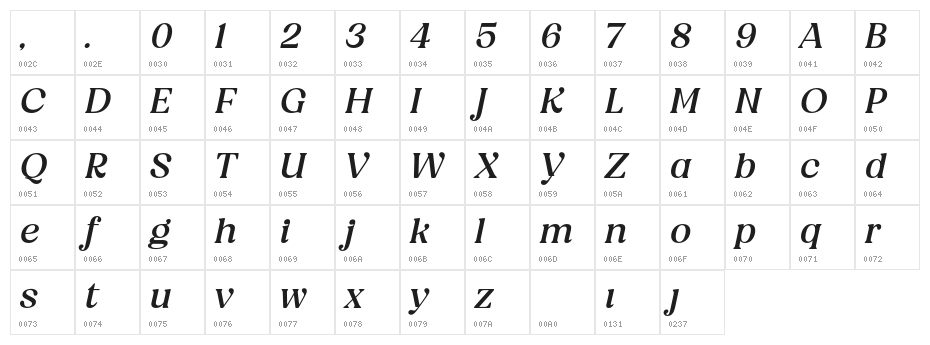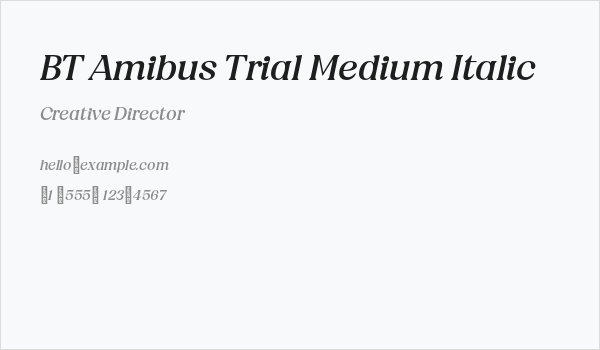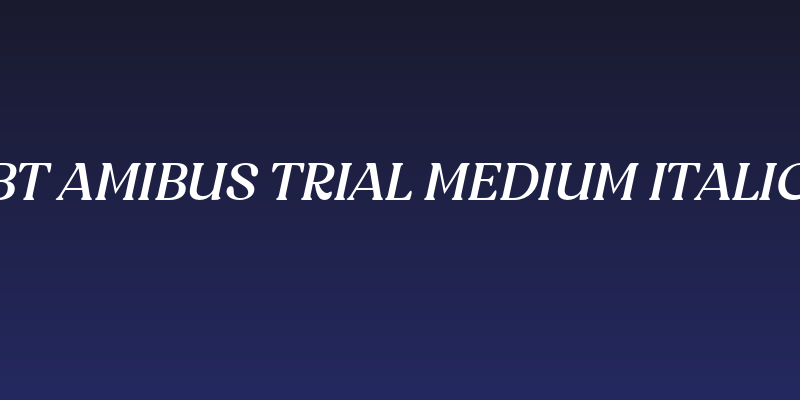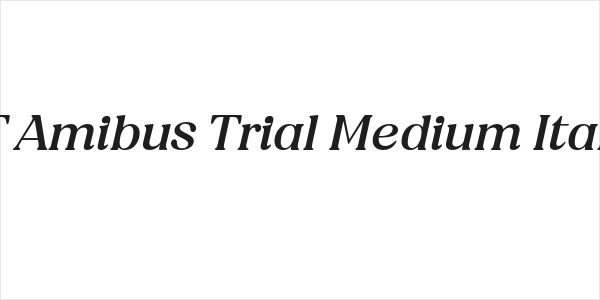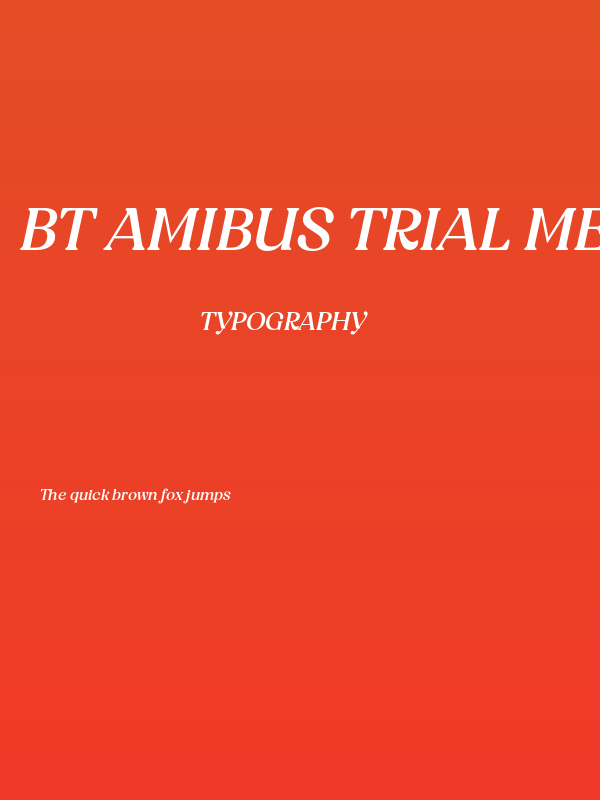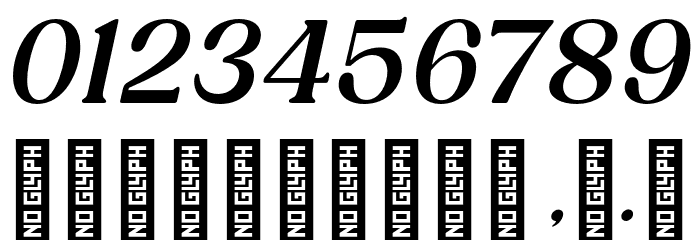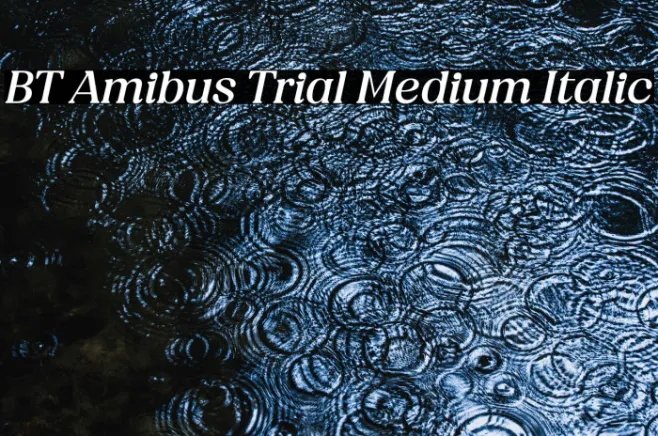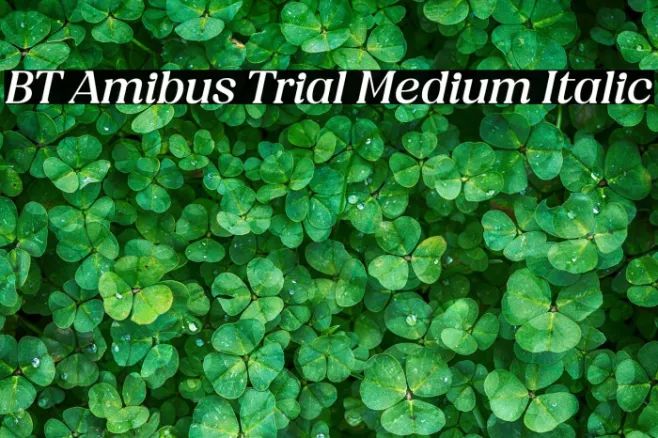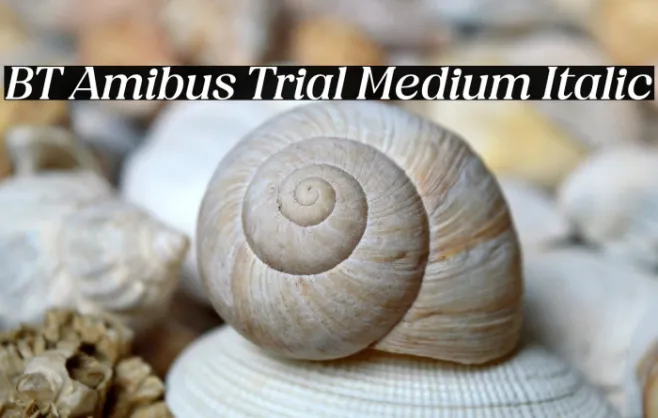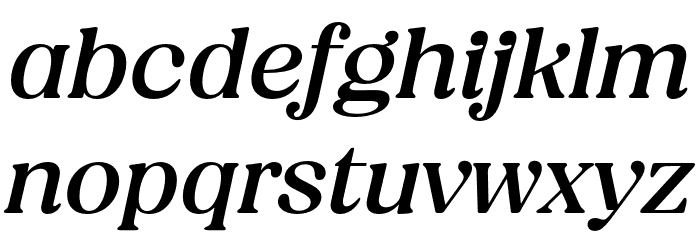
BT Amibus Trial Medium Italic Font
| Gesamtstil | Classic |
| Anwendungsfall | Headlines, Body text, Logos |
| Vorgeschlagene Projekte | Ideal for use in formal invitations, elegant branding, editorial design, and sophisticated advertising materials. |